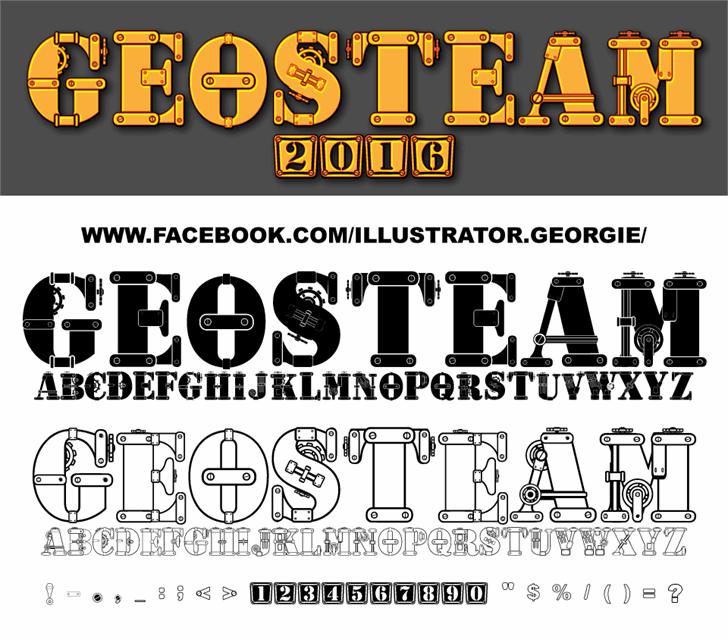
Geosteam Font
A Geosteam Font é uma criação inovadora do designer Hamilton, disponível gratuitamente para trabalhos não comerciais. Esta fonte truetype apresenta os efeitos futuristas dos anos 2000, misturados com elementos de steampunk clássicos. A Geosteam oferece um visual único que combina linhas geométricas modernas com detalhes de engenharia do século passado, criando um efeito retro-futurista impressionante. Ideal para criar design gráfico em estilos vintage ou futuristas, esta fonte surge como uma excelente opção para projetos digitais. Seja em design de logotipos, criações web ou editoriais gráficas, Geosteam oferece um aspecto distintivo e impecável que complementará sua marca de forma original e elegante. Acreditamos que a Geosteam é uma ferramenta valiosa para artistas digitais, fornecendo o elemento único necessário para tornar qualquer projeto especial. Com design minimalista e estilizado, Geosteam é a escolha perfeita para aqueles buscando personalidade em seu trabalho.